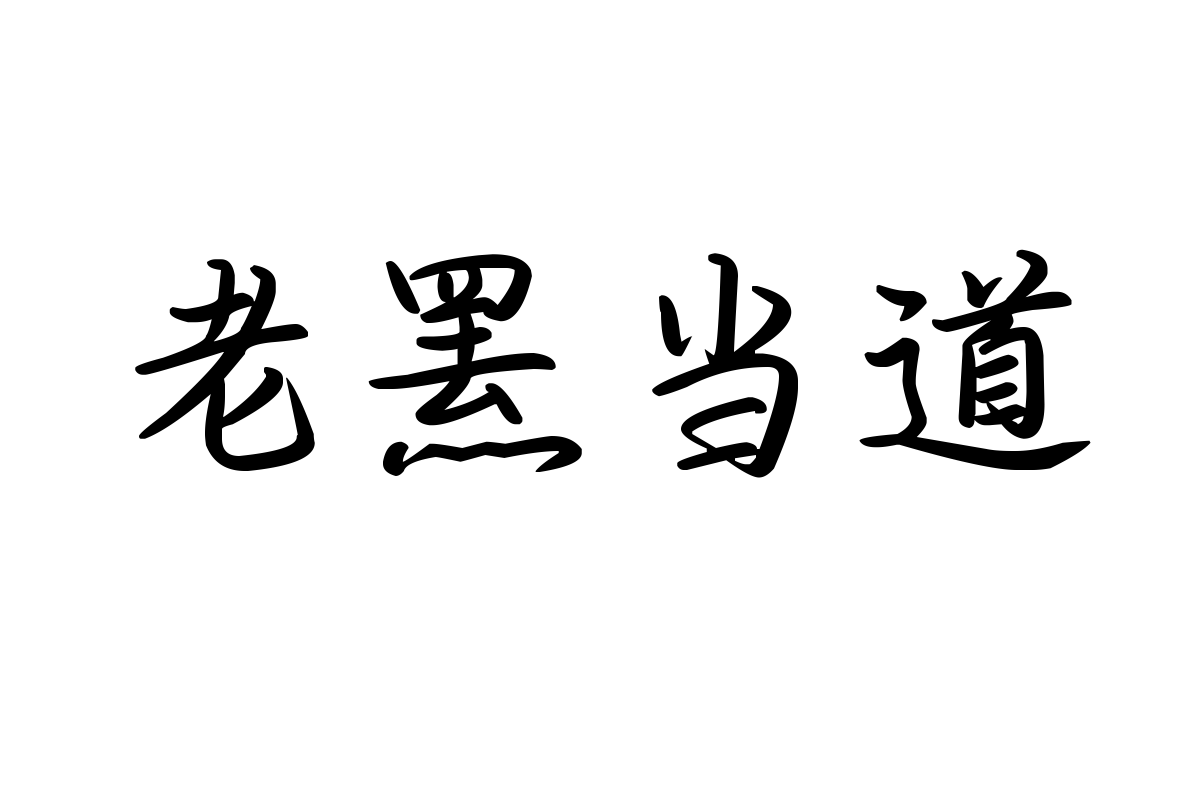
也字工厂小重山行楷字体是一种具有艺术感的书法字体,它采用了传统的行楷风格,结合了现代的设计元素。这种字体的特点是笔画流畅,结构紧凑,线条粗细变化丰富,既有力度又有美感。
也字工厂小重山行楷字体的特点包括:
1. 笔画流畅:这种字体的笔画流畅自然,没有僵硬的感觉,给人一种轻松愉悦的感觉。
2. 结构紧凑:这种字体的结构紧凑,每个字都写得非常紧凑,使得整个字形显得整齐有序。
3. 线条粗细变化丰富:这种字体的线条粗细变化丰富多样,既有粗犷有力的部分,也有细腻柔和的部分,使得整个字体既有力量感又不失美感。
4. 既有力度又有美感:这种字体既有力度,每个字都写得很有力度,但又不失美感,使得整个字体既有艺术感又很实用。
总的来说,也字工厂小重山行楷字体是一种非常有特色的书法字体,它既有传统行楷的韵味,又融入了现代的设计元素,使得整个字体既有艺术感又很实用。